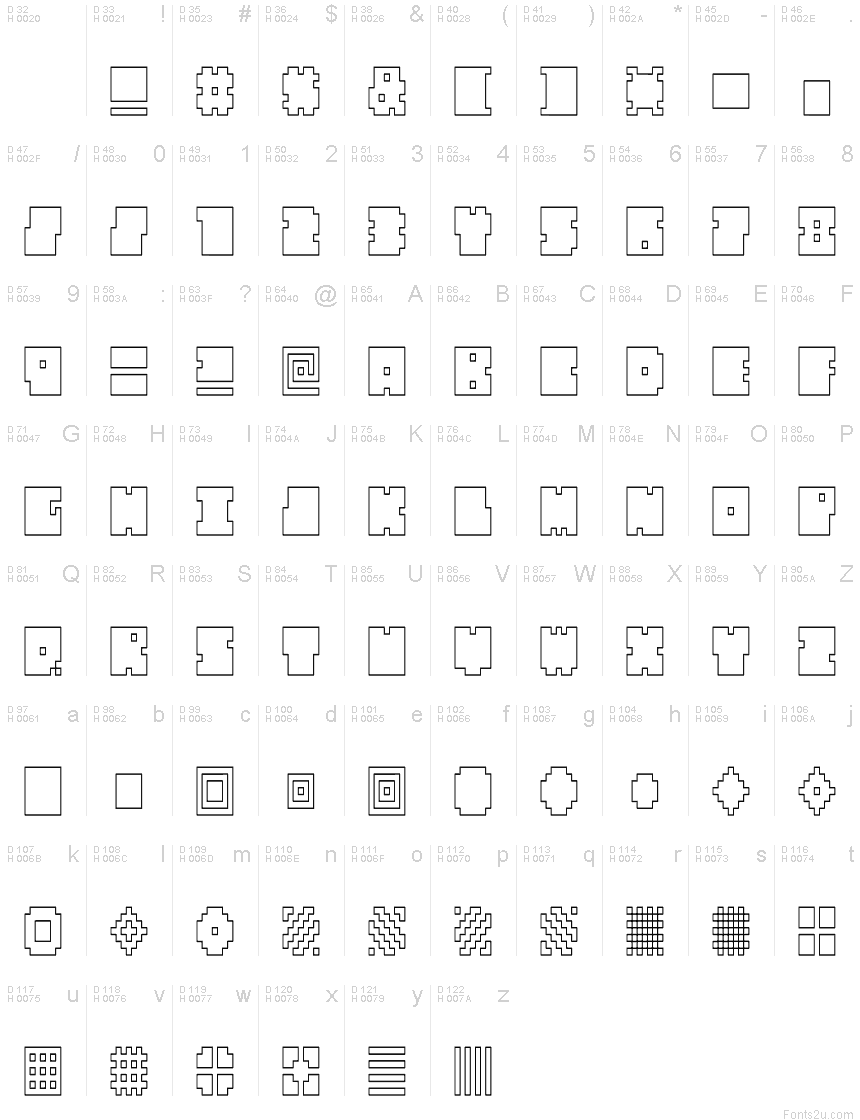
Qube Hollow Thin autorstwa Dana Reddinga z B/W Fontworks to darmowy krój pisma typu display w stylu techno z obrysem, zbudowany z szerokich, prostokątnych form. Jego kanciaste kontury i cienkie linie nadają literom wygląd pustych w środku paneli lub wyciętych maszynowo płyt. Małe prostokątne nacięcia przełamują skądinąd solidną geometrię.
W przypadku interfejsów gier i grafiki muzyki elektronicznej kanciasta konstrukcja może sugerować przełączniki, obudowy obwodów lub oznaczenia przemysłowe. Te same panelowate kształty sprawdzają się również na plakatach science-fiction, gadżetach do gier arcade oraz w identyfikacji wizualnej wydarzeń technologicznych, gdzie napisy mogą stać się częścią schematycznej lub modułowej ilustracji.